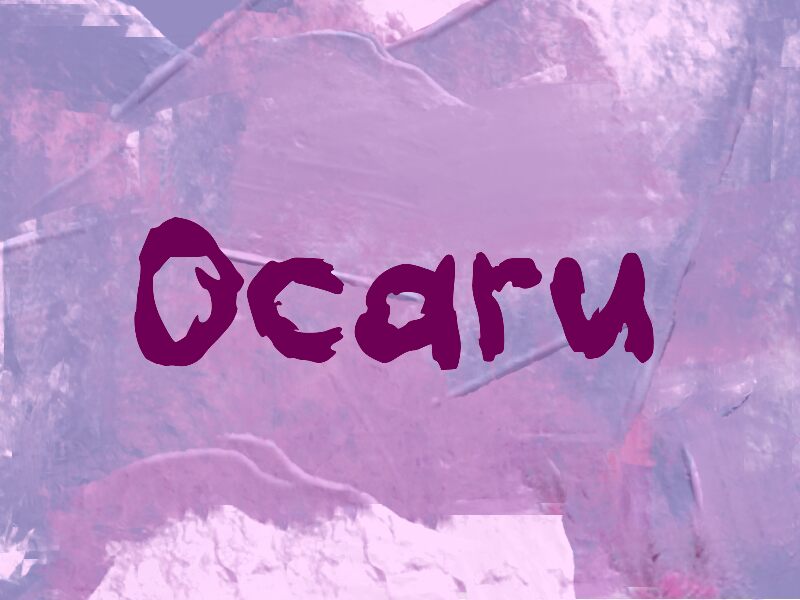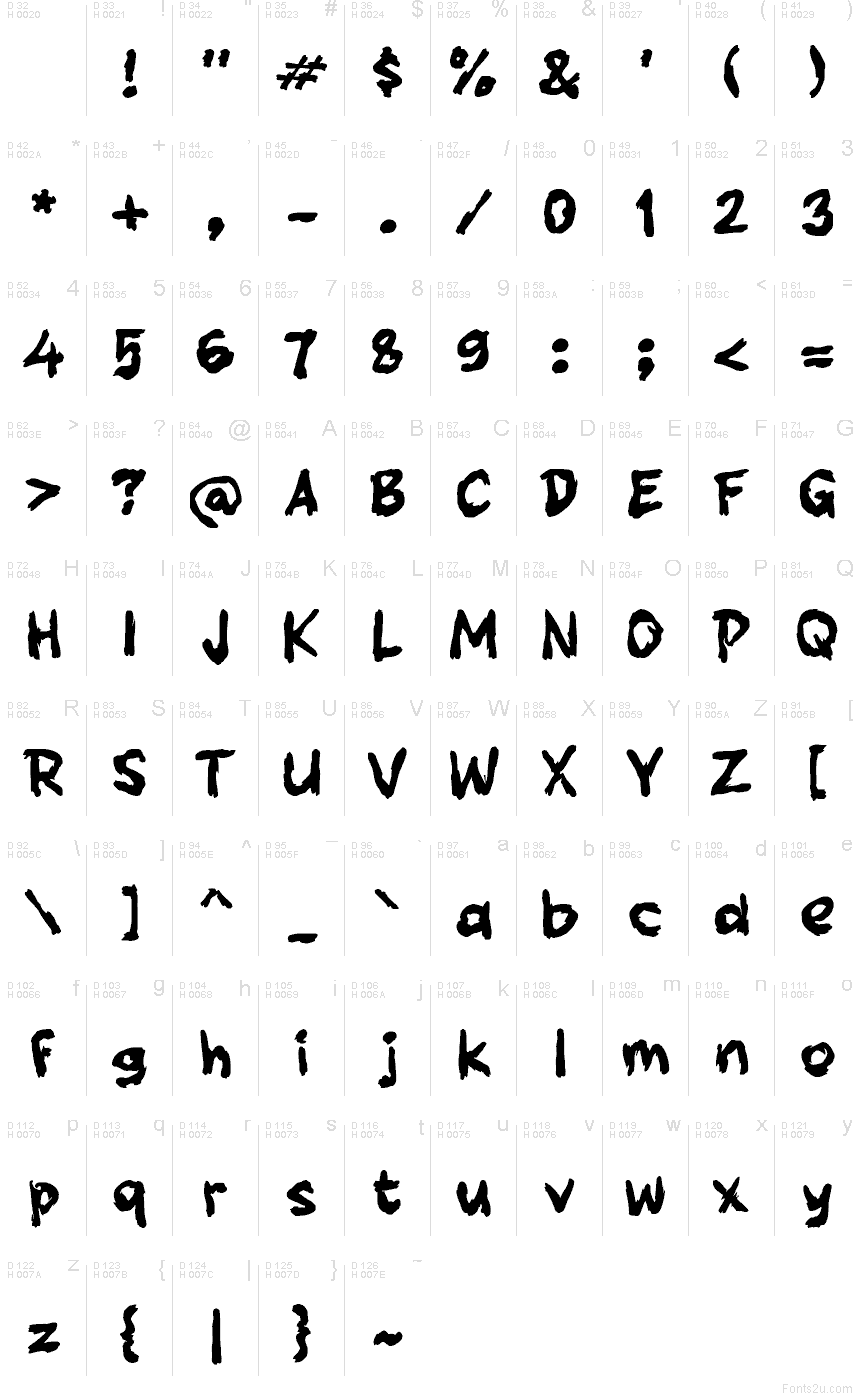
Ocaru від Wep - це безкоштовний пензлевий шрифт, сформований густими, насиченими фарбою мазками та рваними краями, завдяки чому літери виглядають так, ніби їх вирізали з вологої фарби. Текстура залишається грубою та неоднорідною в усьому накресленні; округлі форми, рвані контури та невеликі розриви всередині знаків не дають шрифту виглядати як звичне, відшліфоване письмо.
Ця шорстка поверхня робить його ідеальним для коротких текстів на музичних плакатах, скейтерській графіці, обкладинках зінів, стікерах чи у streetwear-брендингу. Ocaru чудово впишеться в оформлення упаковки або заголовки соцмереж, де ритмічні мазки пензля допомагають словам виглядати безпосередньо, «хендмейдово» та трохи зухвало.
Ocaru
Презентація та наочний зразок шрифту Ocaru
Таблиця символів шрифту Ocaru
Таблиця символів Ocaru: Базова латиниця, сторінка 1
Гліфи шрифту Ocaru — Базова латиниця, сторінка 1